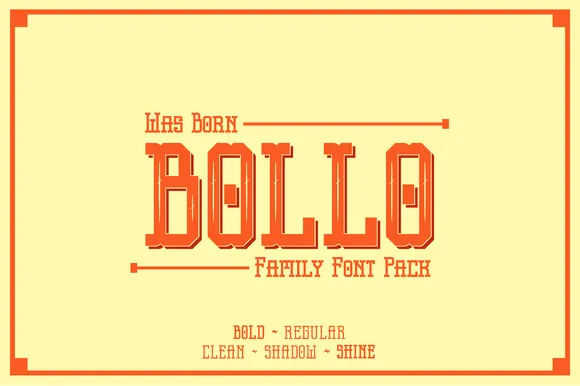
A Bollo Typeface é uma nova adição à família de fonts que chama a atenção por sua fusão moderna com elementos vintage. Inspirada na serifografia clássica, ela oferece um toque nostálgico e elegante para qualquer projeto visual. Esta fonte é perfeitamente adaptável para uso em logotipos, marcas de identidade visual, posters, camisetas personalizadas ou até mesmo cards de agradecimento. Suas linhas sutilmente curvadas criam um contraste arredondado que complementa com mestria os estilos mais tradicionais e atemporais, tornando-a uma escolha ideal para quem deseja adicionar um toque único ao seu trabalho visual. Ideal tanto para designers profissionais quanto para entusiastas do design, a Bollo Typeface oferece um poderoso arsenal de recursos para transformar qualquer projeto em um verdadeiro hit de design.